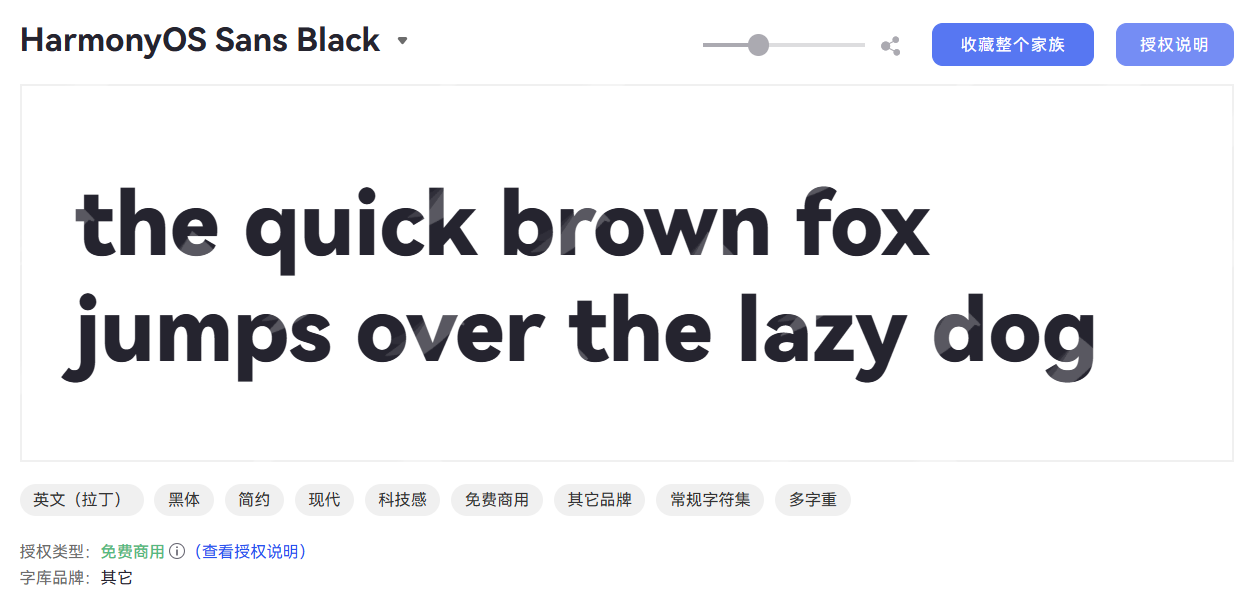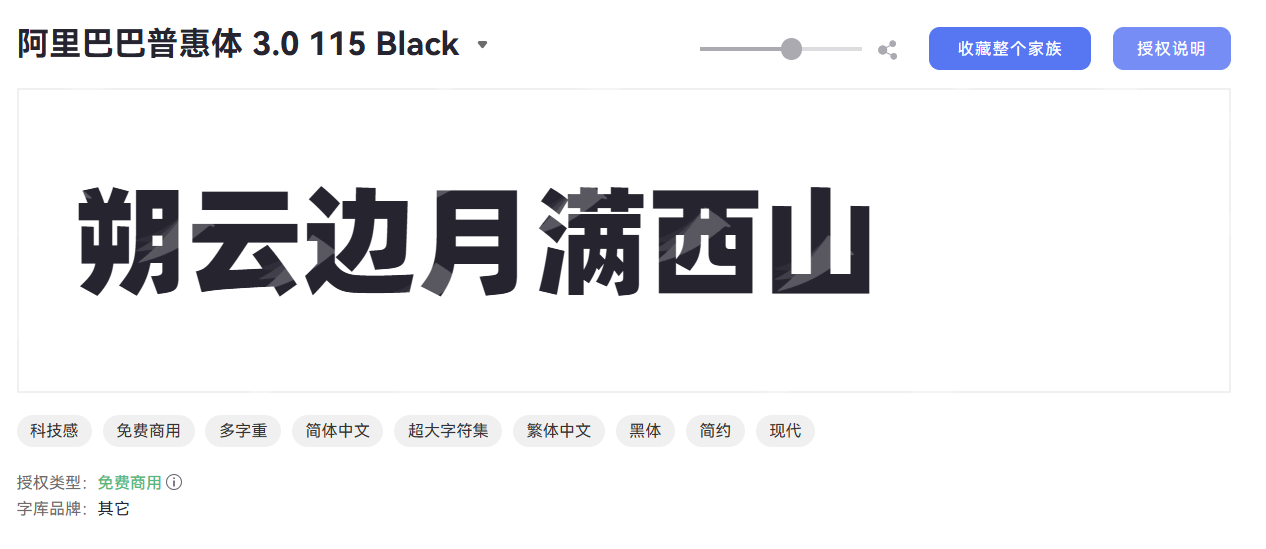
适合影视行业的字体有哪些?8款影视常用字体推荐
对于不同类型的影视内容,字体使用的需求也不相同。例如,商业宣传片通常偏向简洁现代的字体,而年轻化短视频内容则需要更年轻的字体。同时,在实际工作中,字体使用也需要考虑字体授权、管理和使用效率等问题。现在你是不是还没挑选好该使用什么字体?别再犯难啦!本文已经整理好了8 款适合影视行业使用的字体素材,考虑到大家发布的影视内容不同,本文推荐的都是能涵盖大部分影视场景的字体,一起来看吧!。
一、黑体类
1、阿里妈妈方圆体
阿里妈妈方圆体整体风格简洁清晰,在传统黑体基础上融入了更加柔和的字形特点。相比部分偏硬朗的黑体字体,它的视觉感受更加轻松,文字排列后具有较好的平衡感,适合应用于多种影视设计场景。比如电影宣传海报、视频标题、片头字幕以及影视品牌视觉设计中。
在使用时,我们可以根据画面风格搭配不同字号和排版方式,让文字与图片、色彩以及整体构图形成协调关系。如果想使用这款字体,我们可以前往访问【字由】这款拥有正版授权的字体网站,使用时会更加放心。
2、HarmonyOS Sans
HarmonyOS Sans 是一款具有现代设计特点的字体,整体风格简洁,字形比例协调,可以用于视频字幕、片头文字、科技类影片标题以及企业宣传片设计。
而且黑体字体能够适配不同尺寸的屏幕展示,无论是大尺寸海报标题,还是视频中的辅助信息,都能够保持较好的清晰度。该款字体在【字由】中也有提供,想了解更多影视行业常用字体素材,同样可以访问字由官网。
3、阿里巴巴普惠体
阿里巴巴普惠体属于现代黑体类型,字体风格规整,适合商业影视内容使用。它的优势在于字体识别度较高,排版后整体视觉比较稳定。对于需要长期制作系列视频内容的团队来说,统一使用这类字体也有助于保持视觉风格一致。
二、圆体类
4、抖音美好体
抖音美好体的字体风格更加年轻化,线条柔和,具有较强的亲和感。与传统黑体相比,圆体能够降低视觉距离,更适合轻松、温暖、生活化的影视内容。
我们可以将它用于短视频栏目标题、综艺节目包装、品牌故事视频以及年轻用户群体相关的影视内容。它能够让文字呈现更加轻松的视觉效果,同时保持较好的阅读体验。
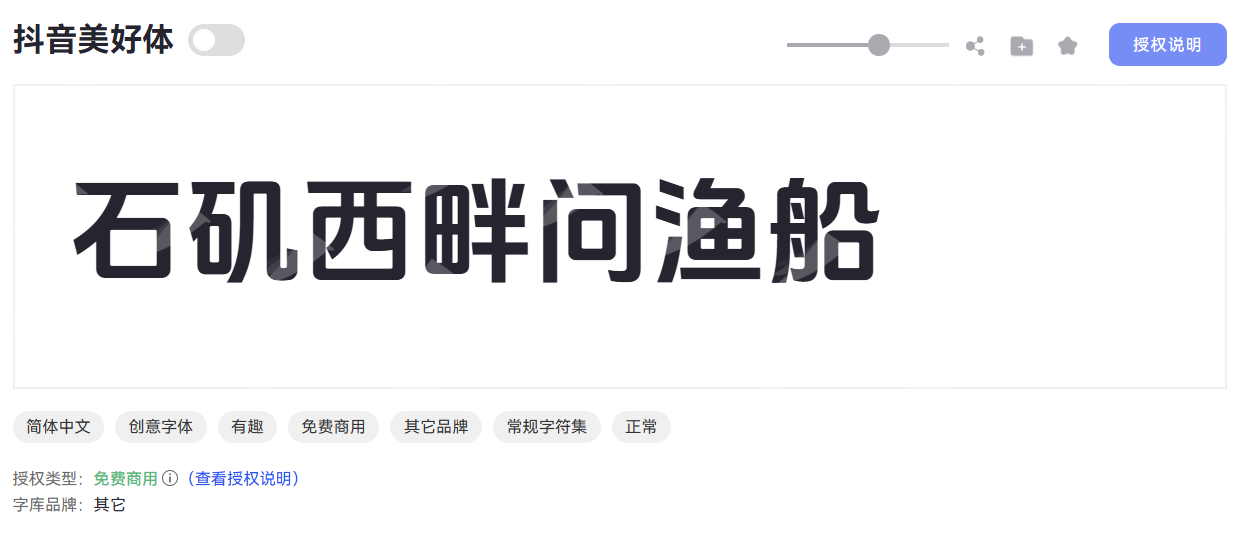
三、楷体类
5、霞鹜文楷
楷体字体通常带有一定的人文气息,比较适合需要表达文化感和故事感的影视作品。它在字形设计上保留了楷体的书写特点,同时进行了现代优化,十分适合数字媒体环境中的使用。对于历史纪录片、文化专题片、文学改编作品等内容,霞鹜文楷能够帮助画面增加温和、细腻的视觉氛围。
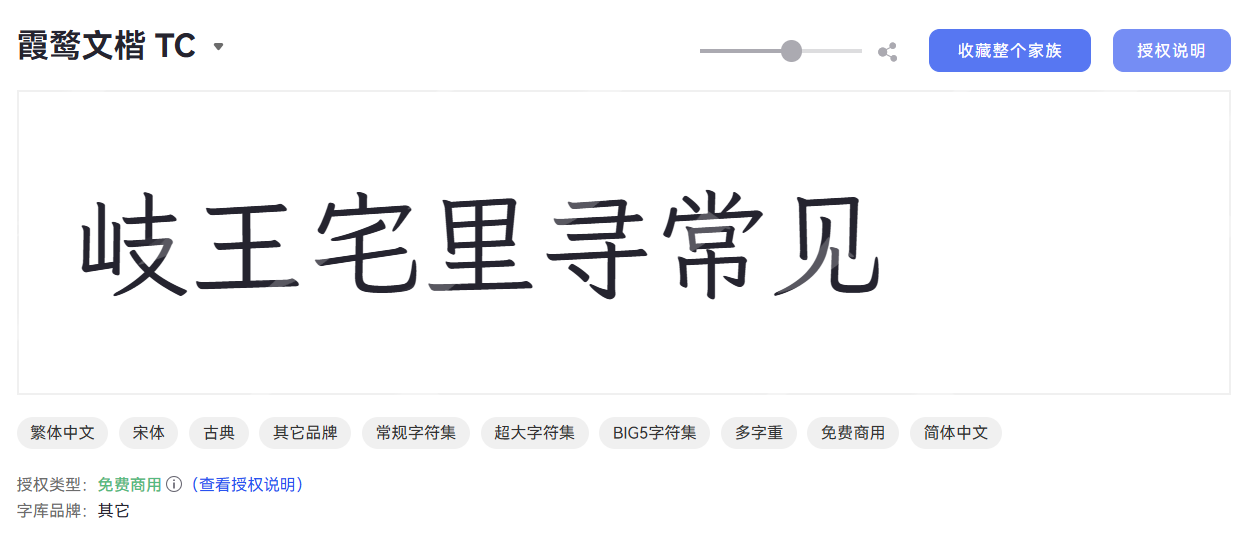
四、宋体类
6、思源宋体
思源宋体是一款具有传统文字风格的字体,它的笔画特点能够带来较强的阅读感和正式感,因此常见于纪录片、文化类节目以及具有叙事属性的视频内容。当然,我们还可以将它与摄影画面、历史素材等元素结合,营造更加有故事感的视觉效果。
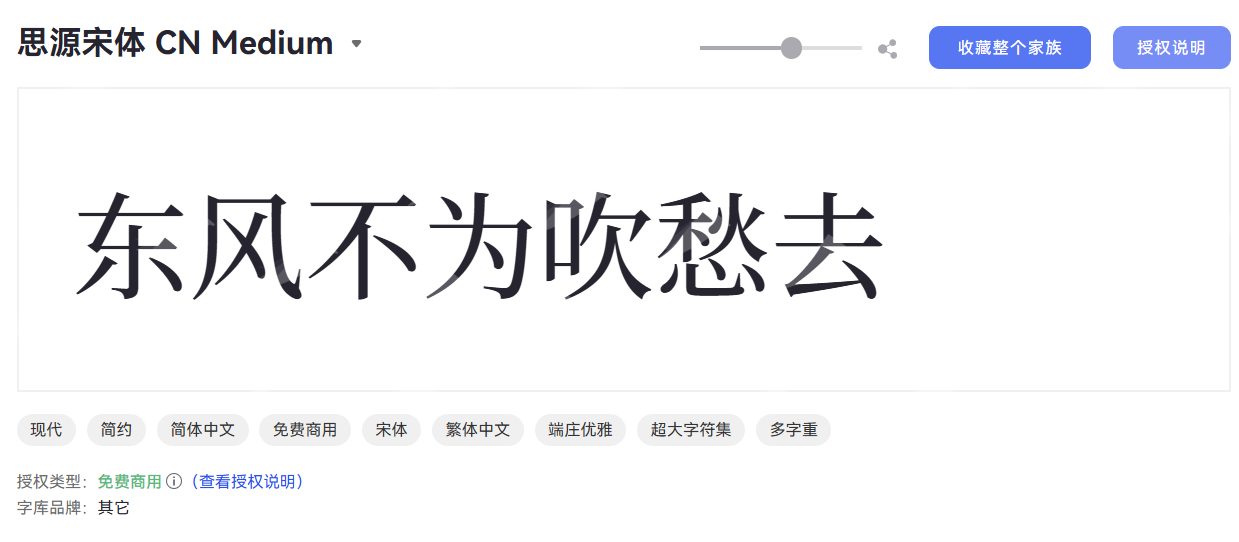
五、手写类
7、演示秋鸿楷
手写字体能够为影视画面增加情绪表达,适合用于青春电影、情感短片、个人故事类视频等场景。演示秋鸿楷具有一定的书写感,能够让文字看起来更加自然。在影视设计中,手写字体通常不会承担大量信息展示,而是作为标题、片尾寄语或者特殊文字元素出现。合理使用后,可以增强作品的情感表达,让画面更加具有个人特色。
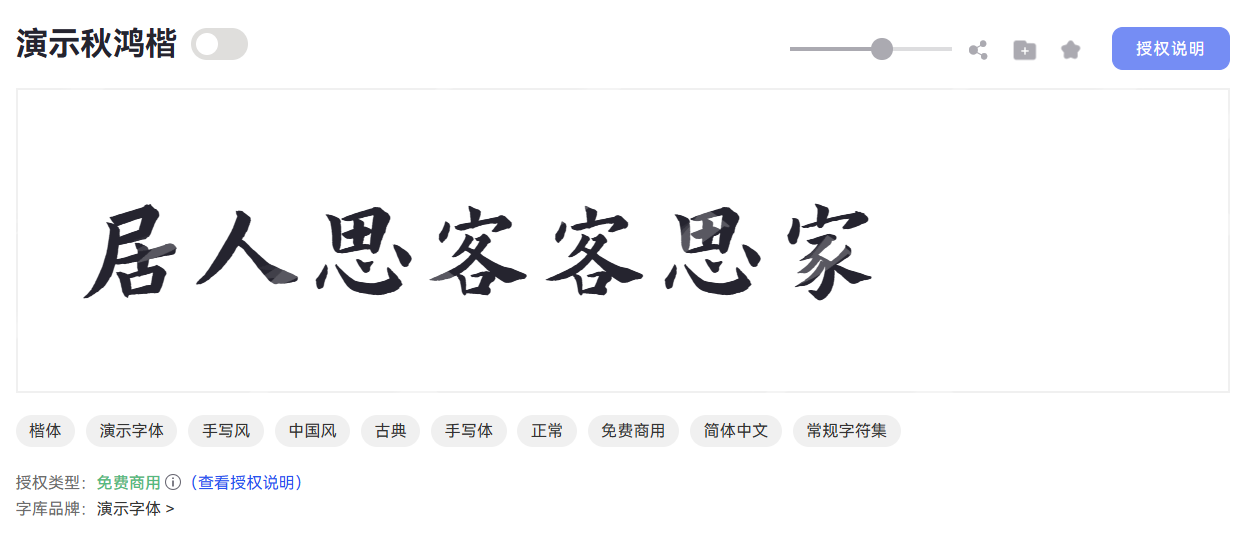
六、创意类
8、庞门正道标题体
庞门正道标题体属于偏创意方向的字体,适合用于需要突出视觉冲击的影视标题设计。它的字体造型具有较明显的设计特点,可以应用在短视频封面、活动宣传片、潮流内容包装等场景中。当然,使用创意字体时,需要结合影视作品主题进行判断。如果画面本身较为丰富,字体设计则需要适当控制,避免影响主要内容展示。